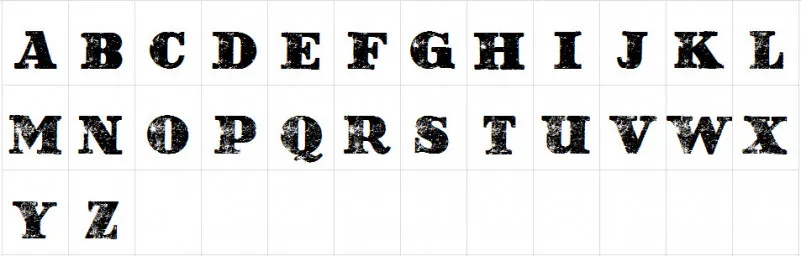
Western Grungy é uma elegante fonte despojada que carrega consigo uma atmosfera vintage mas com toques modernos. Criada por Marta van Eck Designs em 2015, essa fonte traz um toque único e não convencional à sua tipografia. Suas letras apresentam traços rústicos e desorganizados que refletem o charme de uma cidade do interior americano ou a atmosfera selvagem da fronteira do Oeste norte-americano, mas em um formato mais contemporâneo. Ideal para designers que buscam adicionar um toque distinto e pessoal à suas criações, Western Grungy oferece uma maneira única de incorporar elementos artesanais na digitalidade. Esta fonte também é perfeita para designers gráficos que estão procurando por algo diferente para dar a impressão de seu trabalho, seja ele um projeto de site, design de materiais ou até mesmo ilustrações, onde as letras carregam uma história e uma personalidade única.